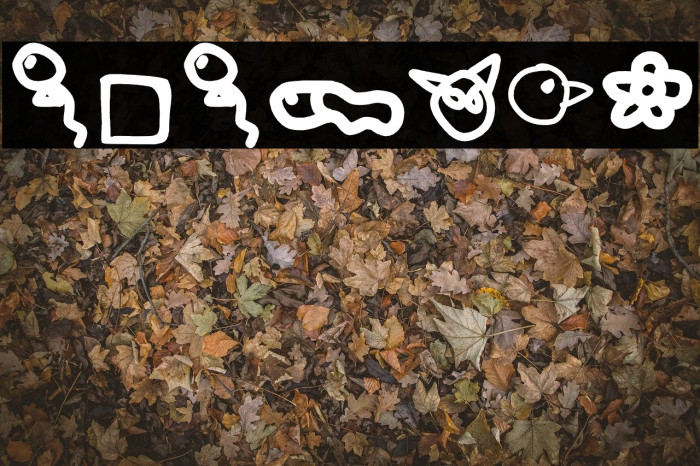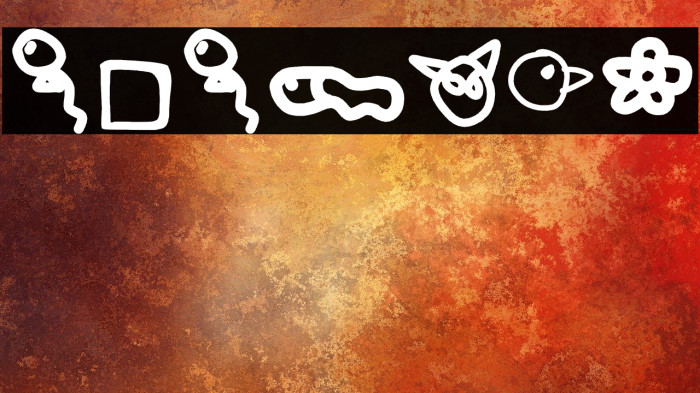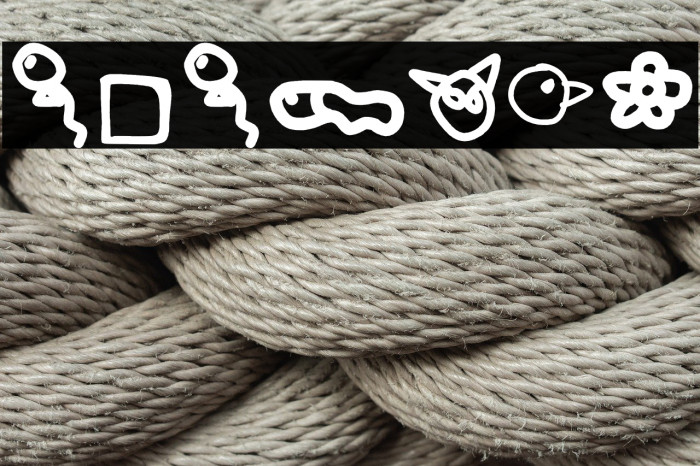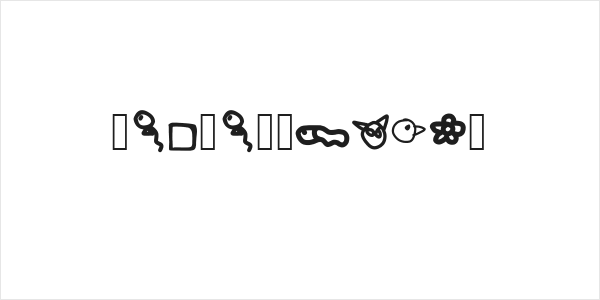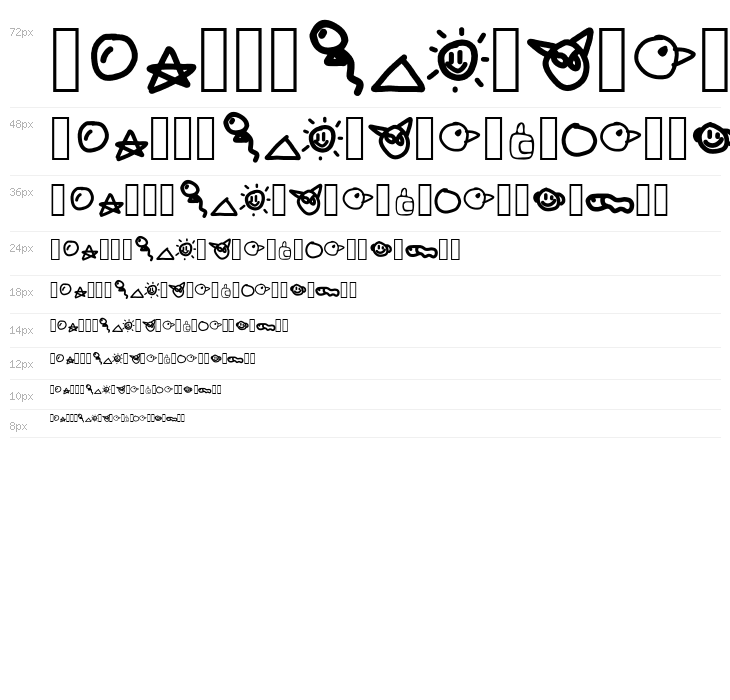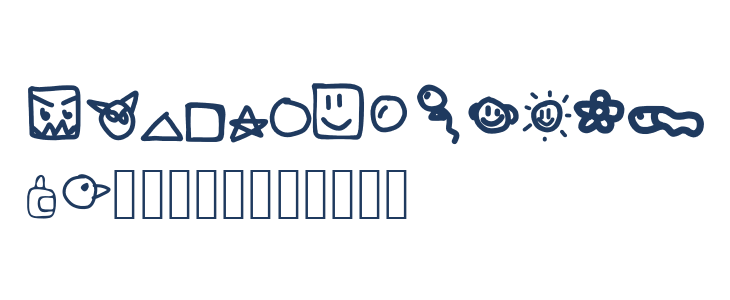
KidPixymbols Font
Diese Schriftart enthält 20 Zeichen. Klicken Sie auf ein Zeichen für Details.
| Gesamtstil | Whimsical, Playful |
| Anwendungsfall | Creative projects, Illustrations, Branding |
| Vorgeschlagene Projekte | Ideal for children's book illustrations, educational materials, playful branding, or creative art projects. |